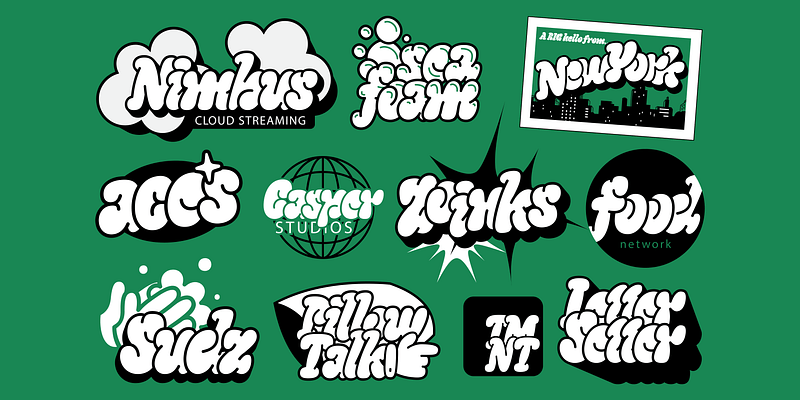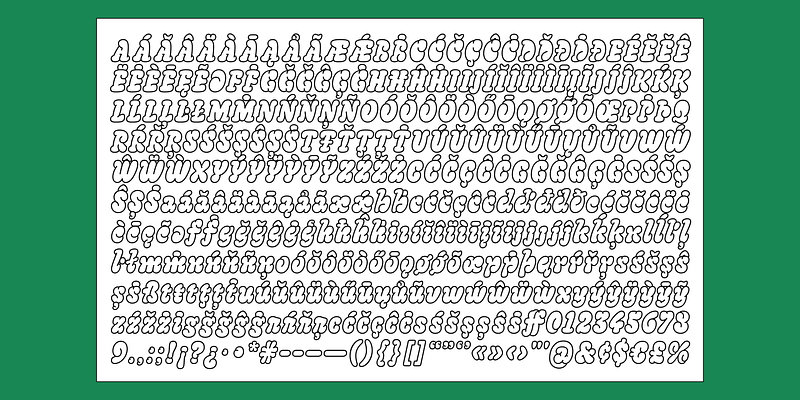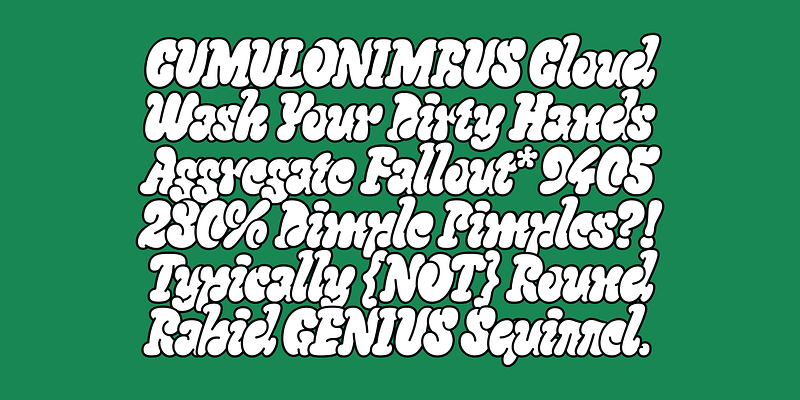
Sudz ist eine von Graffiti und Blasenbuchstaben inspirierte Farbschrift. Sie besteht aus gewundenen und geschwungenen Strichen, die eine dynamische und hypnotische Textur erzeugen.